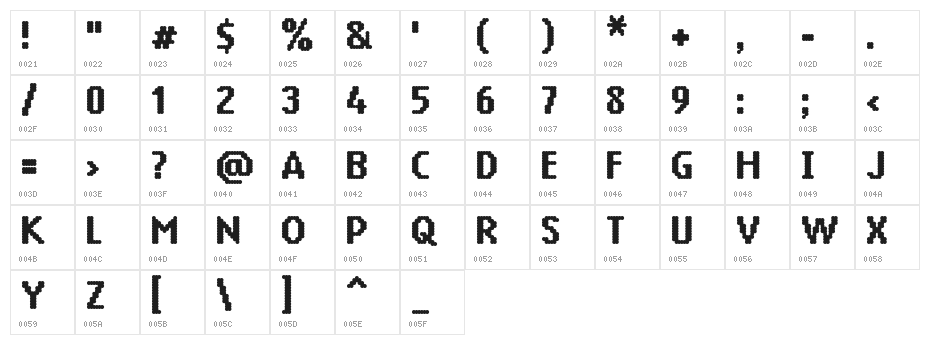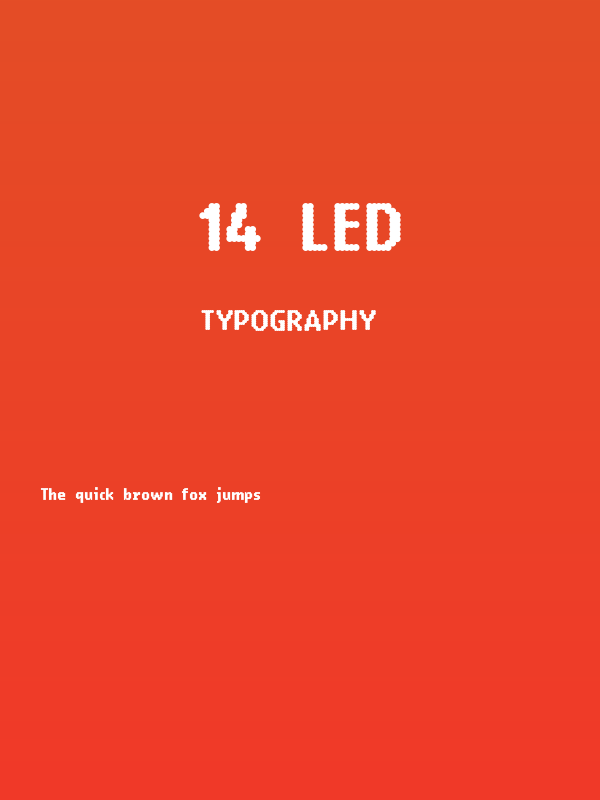
14 LED Font
| Catégories | Pixel |
| Cas d'utilisation | Headlines, Logos, Digital Displays |
| Projets proposés | Ideal for retro-themed designs, tech branding, digital displays, and creative posters. |